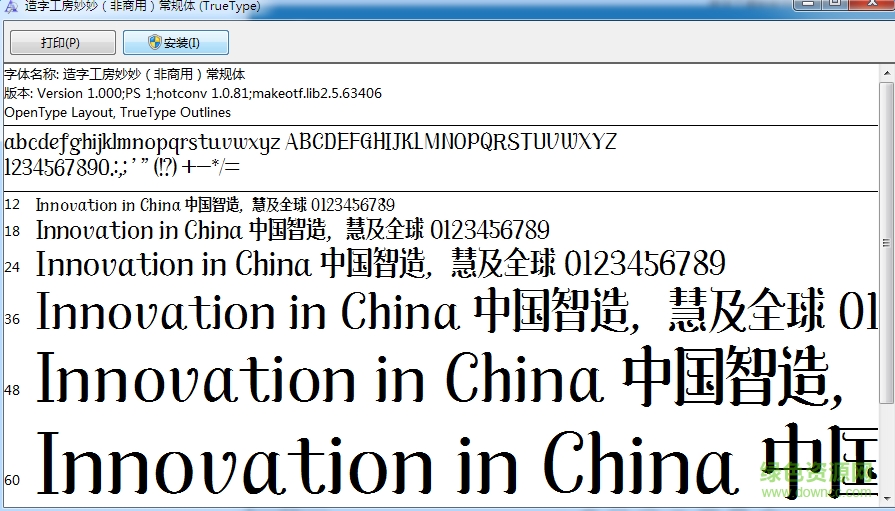
造字工房妙妙粗體是一款非常有特色的藝術(shù)字體,適用于文字標(biāo)題、廣告設(shè)計(jì)、企業(yè)宣傳等視覺(jué)環(huán)境,有著極強(qiáng)的應(yīng)用空間,有需要的朋友可以來(lái)綠色資源網(wǎng)下載試用!
造字工房妙妙體,字形活潑、飄逸靈動(dòng)、端秀清新、特點(diǎn)明確,撇、捺、點(diǎn)、勾大范圍的弧度增加筆畫(huà)的流暢性。捺與鉤上特點(diǎn)的添加與橫豎筆畫(huà)特點(diǎn)相互呼應(yīng),加上結(jié)構(gòu)的細(xì)膩處理使字形更顯俊美挺秀之氣。具有極強(qiáng)的時(shí)尚感。